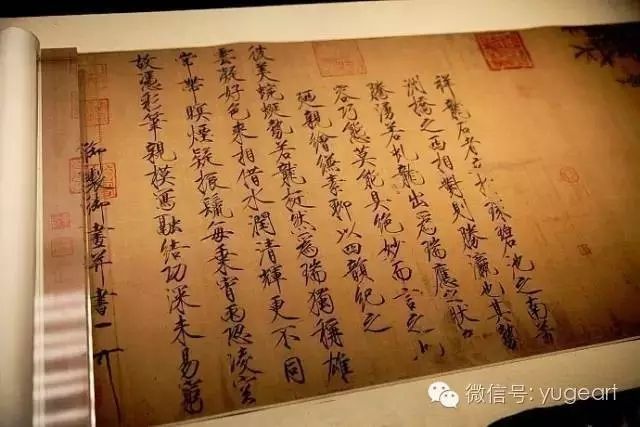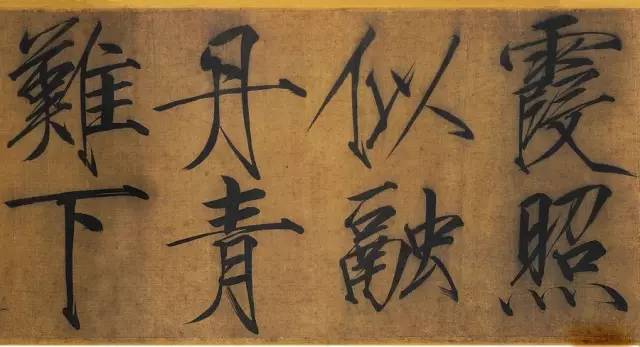
两位皇帝创造的书法新字体!
历史上有两位皇帝别出心裁,不遵照已有的书法字体,而是根据自己的笔法独创了两种字体,这么任性的皇帝你猜是哪两位?
宋徽宗和瘦金体
宋徽宗自创了一种书法字体被后人称之为“瘦金体”,亦称“瘦金书”或“瘦筋体”,也有“鹤体”的雅称,与其所的画工笔重彩相映成趣。宋徽宗是古代少有的艺术天才与全才,渔公子曾在以前介绍过:他除了当皇帝,什么都会!被后世评为“宋徽宗诸事皆能,独不能为君耳!所以开创新字体,完全像他会干出来的事。
瘦金体运笔飘忽快捷,笔迹瘦劲,转折处可明显见到藏锋,是一种风格相当独特的字体。此书体以形象论,本应为“瘦筋体”,以“金”易“筋”,是对御书的尊重。现代美术字体中的“仿宋体”就是模仿瘦金体神韵而创的。
这种瘦挺爽利、侧锋如兰竹的书体,是需要极高的书法功力和涵养,以及神闲气定的心境来完成的,当然也不是别人易于仿造的。后代习其书者甚多,然得其骨髓者寥若晨星。
汉章帝和章草
汉章帝也许大家不是很熟悉,但汉明帝、汉章帝是汉朝皇帝历史上少有的吏治清明,经济发展,社会稳定的时期,史称"明章之治"。但他非常年轻就去世了,只活到三十一岁。
汉章帝的草书非常有名,后世流行的“章草”,据说就是由于刘炟的爱好而形成的一种书体。章草是早期的草书,始于汉代,“今草”的前身。由草写的隶书演变而成。与”今草”的区别主要是保留隶书笔法的形迹,上下字独立而不连写。
章草又叫“急就书”,原因就是章草是对隶书的改革、简化而成的,是一种书写比较快捷的书体,其实章草的产生就是因为事情急迫而潦草书写的。“章草“因其别具一格,且有古朴厚重的特点,近两千年来,深受书家的青睐。
虽然章草是由于汉章帝刘炟的爱好和推行而来,但章草应该不是一时一人所创造,它是从秦代的草隶中演化出来的,经过长期流行通用,继而约定俗成。